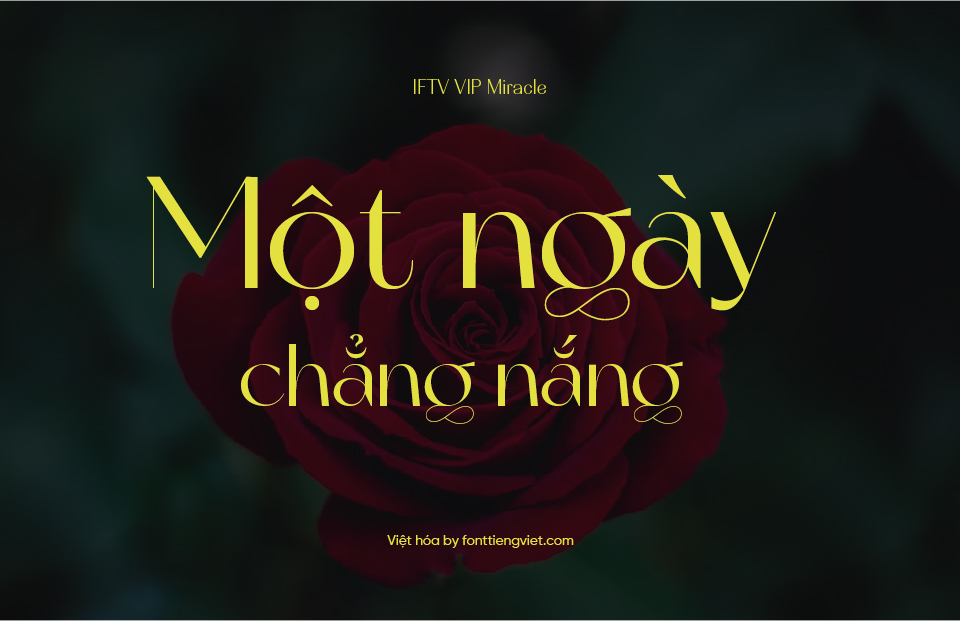
Tải Ngay Bộ Font Việt hóa 1FTV VIP Miracle Đẳng Cấp Cho Thiết Kế Chuyên NghiệpGiới thiệu về bộ Font Việt hóa 1FTV VIP MiracleTrong thế giới thiết kế đồ họa hiện đại, việc lựa chọn một Font Miễn Phí chất lượng luôn là ưu tiên hàng đầu của các designer. Đặc biệt, bộ Font Việt hóa 1FTV VIP Miracle nổi lên như một hiện tượng nhờ sự kết hợp hoàn mỹ giữa nét thanh lịch và tính ứng dụng cao. Đây là bộ font được tinh chỉnh kỹ lưỡng, hỗ trợ đầy đủ bảng mã tiếng Việt, giúp người dùng không còn lo lắng về lỗi hiển thị dấu hay khoảng cách chữ không đều. Với cấu trúc đường nét tinh xảo, Miracle mang đến hơi thở của sự sang trọng, rất phù hợp cho các dự án đòi hỏi tính thẩm mỹ khắt khe như thiệp mời, bìa sách hay các ấn phẩm truyền thông chuyên nghiệp.Những đặc điểm nổi bật của Font Việt hóa 1FTV VIP MiracleThiết kế hiện đại và tinh tếBộ Font Việt hóa 1FTV VIP Miracle sở hữu các đường nét uyển chuyển, tạo nên cảm giác nhẹ nhàng nhưng vô cùng chắc chắn. Sự cân bằng giữa các nét thanh và nét đậm giúp font chữ này giữ được độ rõ nét ngay cả khi hiển thị ở kích thước nhỏ. Các nhà thiết kế thường lựa chọn Miracle cho các tiêu đề chính nhằm thu hút ánh nhìn của người xem ngay từ giây phút đầu tiên. Độ tương phản hợp lý trong cấu trúc chữ giúp nội dung trở nên sống động và có chiều sâu hơn so với các bộ font thông dụng khác.Hỗ trợ tiếng Việt hoàn hảoĐiểm mạnh lớn nhất của Font Việt hóa 1FTV VIP Miracle chính là khả năng hiển thị tiếng Việt mượt mà. Đội ngũ việt hóa đã dành nhiều tâm huyết để vẽ lại các dấu thanh sao cho hài hòa với phong cách gốc của bộ chữ. Điều này cực kỳ quan trọng đối với các bạn học sinh và giáo viên khi soạn thảo tài liệu hay làm slide thuyết trình, giúp bài làm trông chuyên nghiệp và dễ đọc hơn. Bạn sẽ không gặp phải tình trạng các dấu hỏi, ngã bị lệch vị trí hay bị biến dạng khi sử dụng trên các phần mềm như Adobe Photoshop, Illustrator hay Canva.Ứng dụng thực tế của Font Việt hóa 1FTV VIP Miracle trong đời sốngNhờ vẻ ngoài cuốn hút, Font Việt hóa 1FTV VIP Miracle được ứng dụng rộng rãi trong nhiều lĩnh vực khác nhau. Trong môi trường học đường, giáo viên có thể dùng font chữ này để thiết kế các chứng chỉ khen thưởng, tạo động lực cho học sinh. Trong lĩnh vực kinh doanh, Miracle là lựa chọn tuyệt vời cho thiết kế logo, bao bì sản phẩm cao cấp hoặc các banner quảng cáo trên mạng xã hội. Khả năng biến hóa linh hoạt giúp bộ font này thích nghi tốt với cả phong cách cổ điển lẫn hiện đại, mang lại giá trị thương hiệu vượt trội cho người sử dụng.Hướng dẫn cài đặt và lưu ý khi sử dụng font chữViệc cài đặt Font Việt hóa 1FTV VIP Miracle vô cùng đơn giản trên cả hệ điều hành Windows và macOS. Sau khi tải về, bạn chỉ cần giải nén tệp tin, chuột phải vào định dạng font và chọn Install. Để đạt hiệu quả thị giác tốt nhất, bạn nên kết hợp Miracle với một font chữ không chân (Sans-serif) đơn giản cho phần nội dung dài, nhằm tạo ra sự phân cấp thông tin rõ ràng. Hãy luôn kiểm tra bản quyền nếu bạn có ý định sử dụng cho các dự án thương mại lớn để đảm bảo quyền lợi của nhà sáng tạo.Kết luận về bộ Font Việt hóa 1FTV VIP MiracleTóm lại, Font Việt hóa 1FTV VIP Miracle là một công cụ hỗ trợ đắc lực mà bất kỳ ai yêu thích cái đẹp cũng nên sở hữu trong bộ sưu tập của mình. Với sự tỉ mỉ trong khâu việt hóa và phong cách thiết kế đẳng cấp, nó chắc chắn sẽ làm bừng sáng mọi ý tưởng sáng tạo của bạn. Nếu bạn đang tìm kiếm những tài nguyên thiết kế chất lượng nhất, đừng quên ghé thăm trang Font Miễn Phí, Font Việt Hóa, Font Việt hóa 1FTV VIP Miracle để tải về và trải nghiệm ngay hôm nay. Hy vọng bộ font này sẽ mang lại nguồn cảm hứng mới cho các dự án sắp tới của bạn.
Font Việt hóa 1FTV VIP Miracle